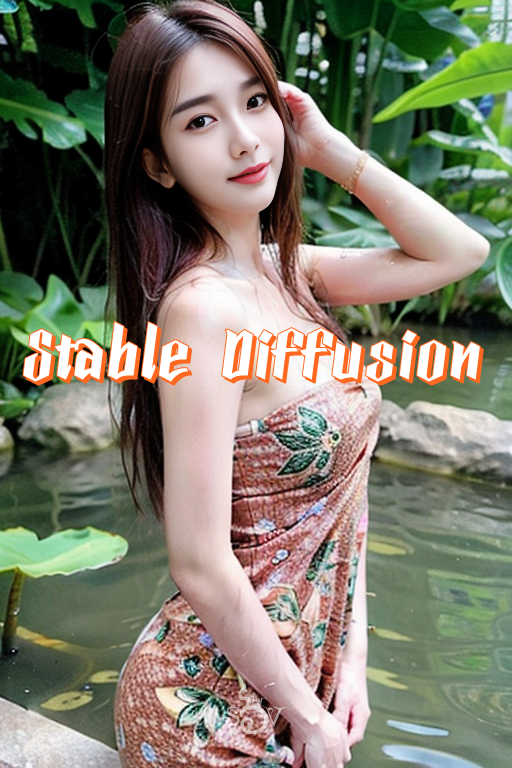
ฟอนต์ ลูกครึ่ง
ฟอนต์ลูกครึ่ง แนวคิดจากตัวเชิงอักษรละตินอวบๆ ปรับเป็นอักษรไทย เปลี่ยนใจเอาเชิงออก บางตัวจะกลมก็ปรับเป็นเหลี่ยม ไม่เอาสักทาง
น่าจะเหมาะกับพาดหัว เลยลองทำเป็นหัวนิตยสาร..
ลองใช้เป็น text พออ่านได้ แต่ถูกด่า (เอามาเบียดบัง นางแบบทำไม)
ชื่อฟอนต์ : ลูกครึ่ง
ฟอนต์ลูกครึ่ง แนวคิดจากตัวเชิงอักษรละตินอวบๆ ปรับเป็นอักษรไทย เปลี่ยนใจเอาเชิงออก บางตัวจะกลมก็ปรับเป็นเหลี่ยม ไม่เอาสักทาง ส่วนภาพประกอบทำได้ทุกอย่างเพราะน้องเป็น AI เน้อ ไม่ใช่ภาพคนจริงๆ